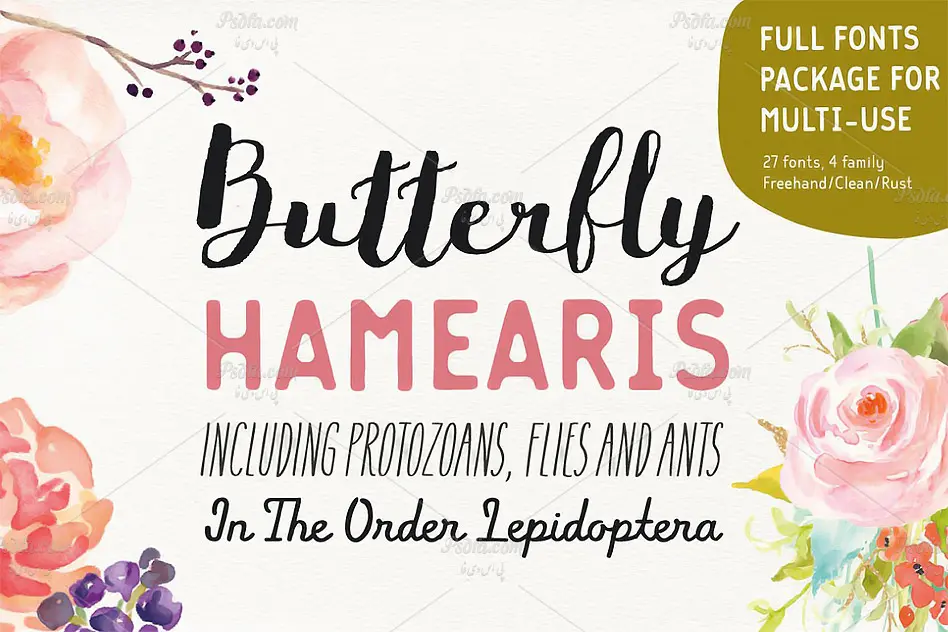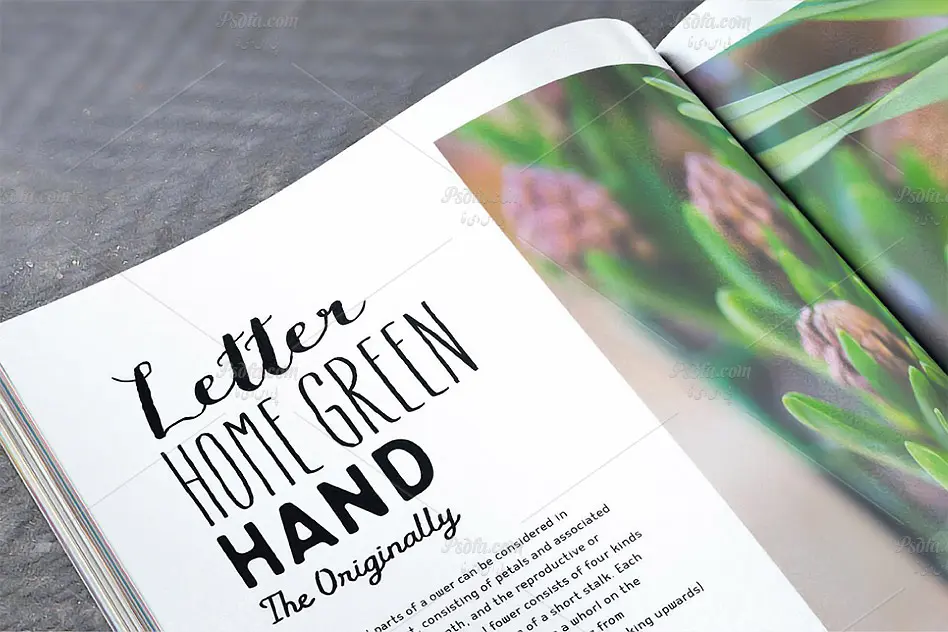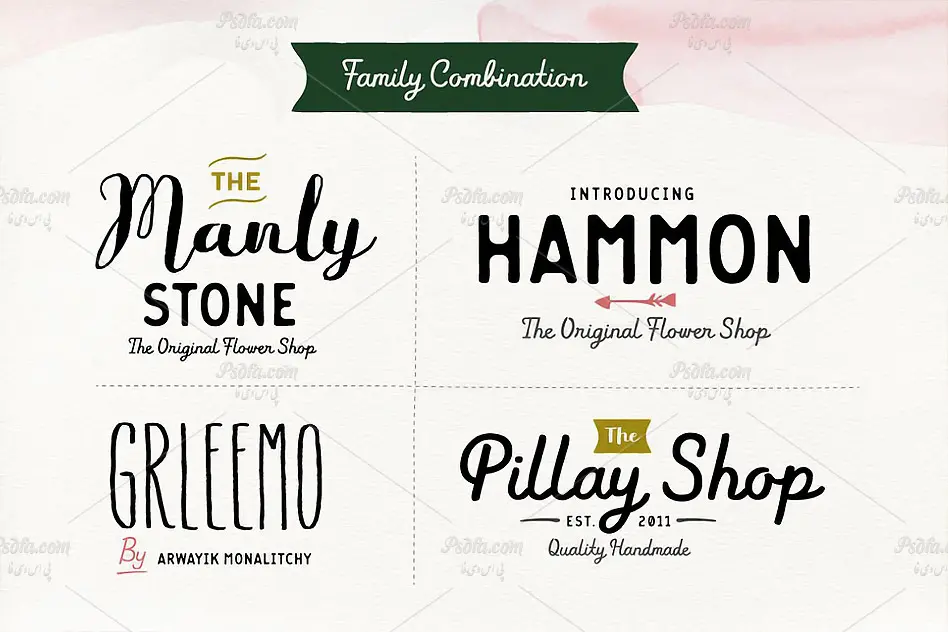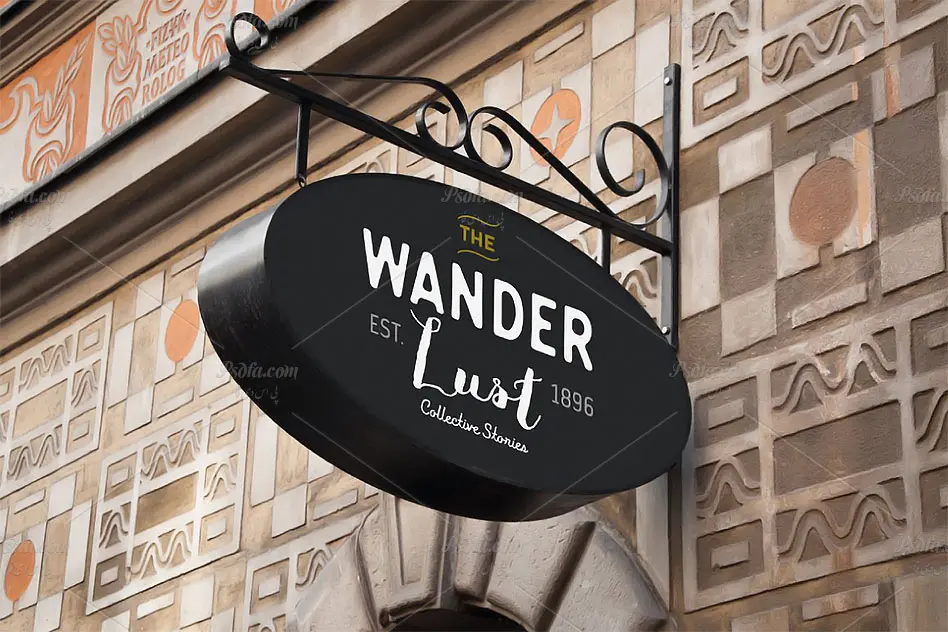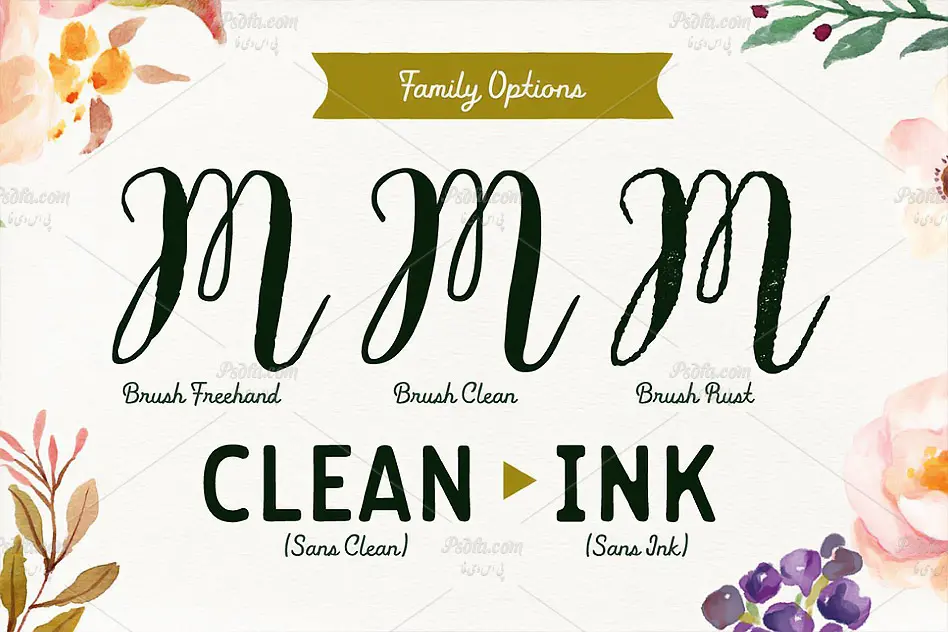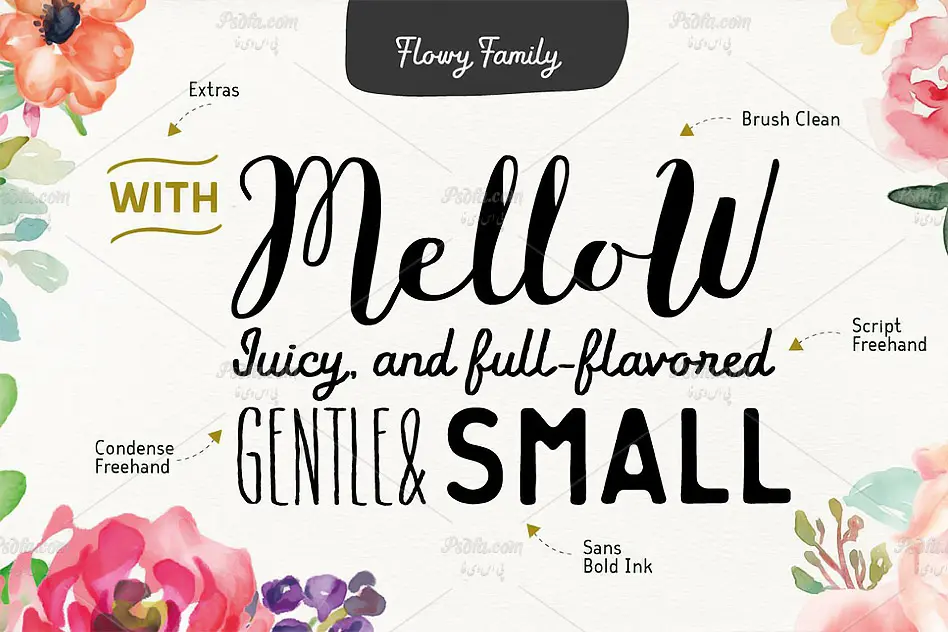
در این مطلب شاهد مجموعه 29 فونت انگلیسی فوق العاده شیک و زیبا با فرمت TTF و OTF جهت استفاده در نرم افزارهای ویرایش متن و همچنین نرم افزارهای گرافیکی می باشید. همانطور که می دانید و قبلا هم در مطالب گذشته ذکر شد فونت ها از ابزارهای بسیار کاربردی در نرم افزارهای گرافیکی همچون فتوشاپ ، ایلوستریتور و … می باشند. با کمک فونت ها مخصوصا فونت های زیبایی مانند این مجموعه (Flowy Fonts Bundle) می توان آثار گرافیکی فوق العاده زیبایی خلق کرد. به همین منظور در این مطلب یک مجموعه از این فونت های زیبا را جهت دانلود رایگان برای شما دوستان قرار داده ایم. برای راحتی در نصب ، فونت ها را در دو مجموعه TTF و OTF قرار داده ایم که پیشنهاد می شود یکی از فرمت ها را در سیستم خود نصب نمائید. برای نصب فونت ها در ویندوز 7 به بالا کافی است بر روی فونت راست کلیک کرده سپس گزینه Install را انتخاب نمائید. امیدواریم از این مجموعه فونت لذت ببرید و در طرح ها و پروژه های خود از آن استفاده کنید. پیش نمایش تعدادی از فونت ها را می توانید در تصاویر زیر مشاهده فرمائید.
- نام فونت : Flowy Fonts Family
- وزن : معمولی (Regular), ضخیم (Bold), طرحدار (Extras), قلمویی (Brush), مورب(Italic)
- سبک : قلمویی, زنگ زده